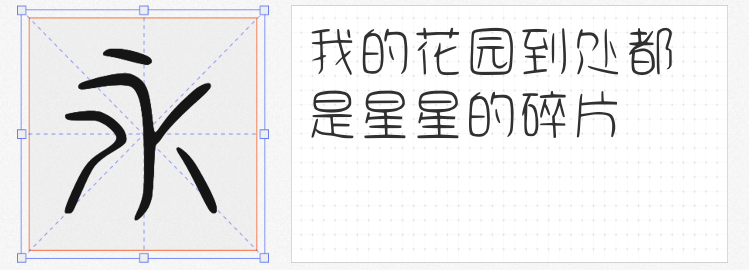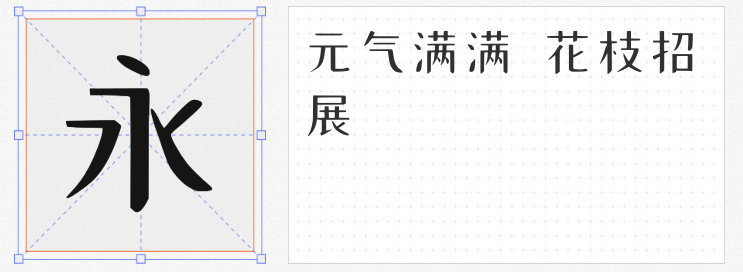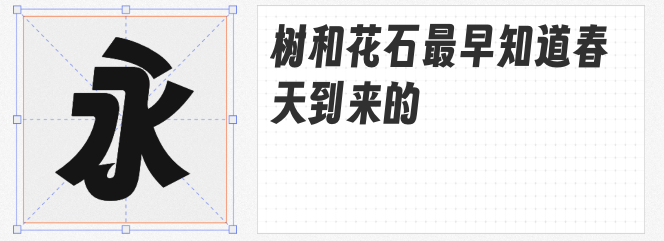
在包装设计的竞技场中,字体不仅是信息载体,更是品牌个性的视觉宣言。以下四款免费商用字体,以独特的设计语言适配不同场景需求,助力设计师打造兼具辨识度与实用性的包装方案。
基于得意黑加粗加宽改造的「字魂扁桃体」,通过标志性“喇叭口”设计将原版的微笑弧度升级为动态卷角,赋予字体跃动的生命力。加粗后的笔画在远距离仍能保持清晰识别,尤其适合食品、潮玩等年轻化产品的主标题设计。其夸张的几何结构与高对比度字重,能在货架陈列中快速抓住消费者视线,同时通过圆角处理避免视觉压迫感,平衡个性与亲和力。
以传统刷墙字体为灵感的「乡立方黑体」,通过重构笔画粗细与字面空间,将乡村文化的质朴感转化为现代设计语言。略带手写感的笔触与均匀的布白,使其既适用于农产品包装的自然叙事,也能通过调整字号适配地域文化衍生品。这款字体在保留传统韵味的同时,通过标准化结构解决了手写字体难以规模化应用的问题,成为连接传统与现代的桥梁。
由AI生成的「字体家AI造字柒恒」字体,以全圆角笔画构建出无棱角的视觉形态,流畅的曲线如同液体流动,传递出温和包容的品牌气质。其低饱和度的视觉张力,使其成为母婴产品、健康食品等品类的理想选择。在需要营造高级感的包装设计中,柒恒可通过与几何图形或留白结合,形成刚柔并济的视觉层次。
以“站酷小薇LOGO体”为基底融合AI生成的「礼品卉自由落体」,通过削减冗余装饰实现极致简洁。垂直笔画的干脆利落与水平笔画的微妙弧度形成微妙对比,在保持易读性的同时注入现代设计感。这款字体适合科技产品、快消品等需要快速传递核心信息的包装场景,其高效的空间利用率可适配复杂信息排版需求。
这四款字体通过差异化设计,覆盖了从传统到现代、从柔和到张扬的全风格谱系。设计师可根据产品调性选择核心字体,并通过字号对比、色彩搭配等手法,构建具有记忆点的包装视觉系统,最终实现品牌信息与消费者情感的精准对接。